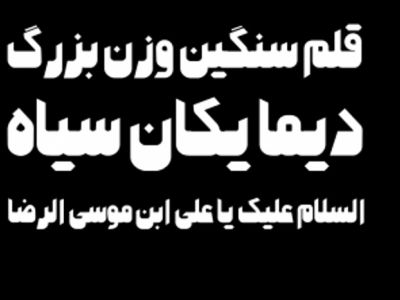
فونت زیبای دیما آرا
فونت عربی آرا جز فونت های جدید عربی است که مناسب طراحی لوگو تایپ می باشد٫ طراح این فونت عبدالله الحربی طراحی سوری می باشد. ما این فونت را برای استفاده شما فارسی سازی کرده و مجدد منتشر کردیم.
قلم زیبای فونت زیبای دیما آرا منتشر شده است.